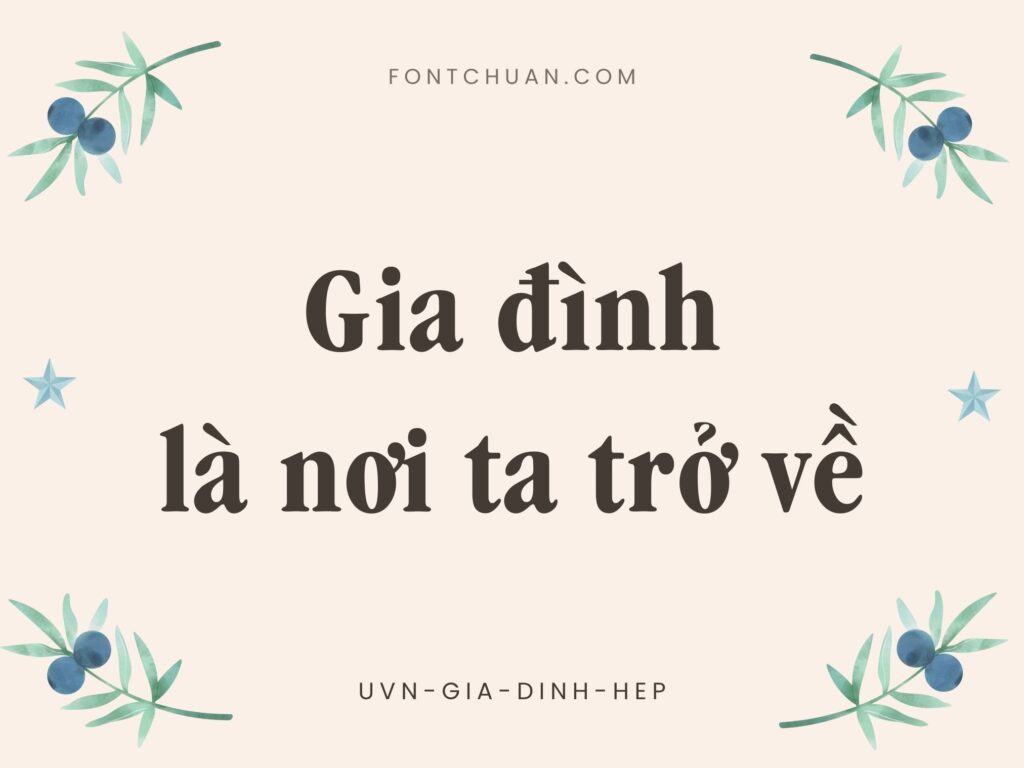
Font UVN Gia Dinh Hep Việt Hóa
UVN Gia Định Hẹp là biến thể condensed của bộ font UVN Gia Định, được thiết kế với mục tiêu tối ưu không gian hiển thị mà vẫn giữ được vẻ trang nghiêm và lịch sự. Kiểu chữ mang hơi hướng truyền thống, phù hợp với những nội dung mang tính học thuật, giáo dục, hoặc mang sắc thái văn hóa, lịch sử. Font này chỉ được sưu tầm và đăng bởi thành viên của Font Chuẩn, nhằm giới thiệu đến cộng đồng thiết kế những lựa chọn đáng tin cậy cho các dự án in ấn hoặc truyền thông.
Thiết kế của UVN Gia Định Hẹp thuộc nhóm serif condensed, các đường nét mạnh mẽ và chắc chắn nhưng vẫn thanh thoát, dễ đọc. Cấu trúc chữ cân đối, phù hợp cho các tiêu đề, nội dung trên sách giáo khoa, báo chí, hoặc brochure có diện tích hẹp. Font phù hợp với ngành giáo dục, quảng cáo, công nghệ, bất động sản và ẩm thực. Sự kiện nên dùng là ngày Nhà giáo, Tết, lễ hội, Trung thu.